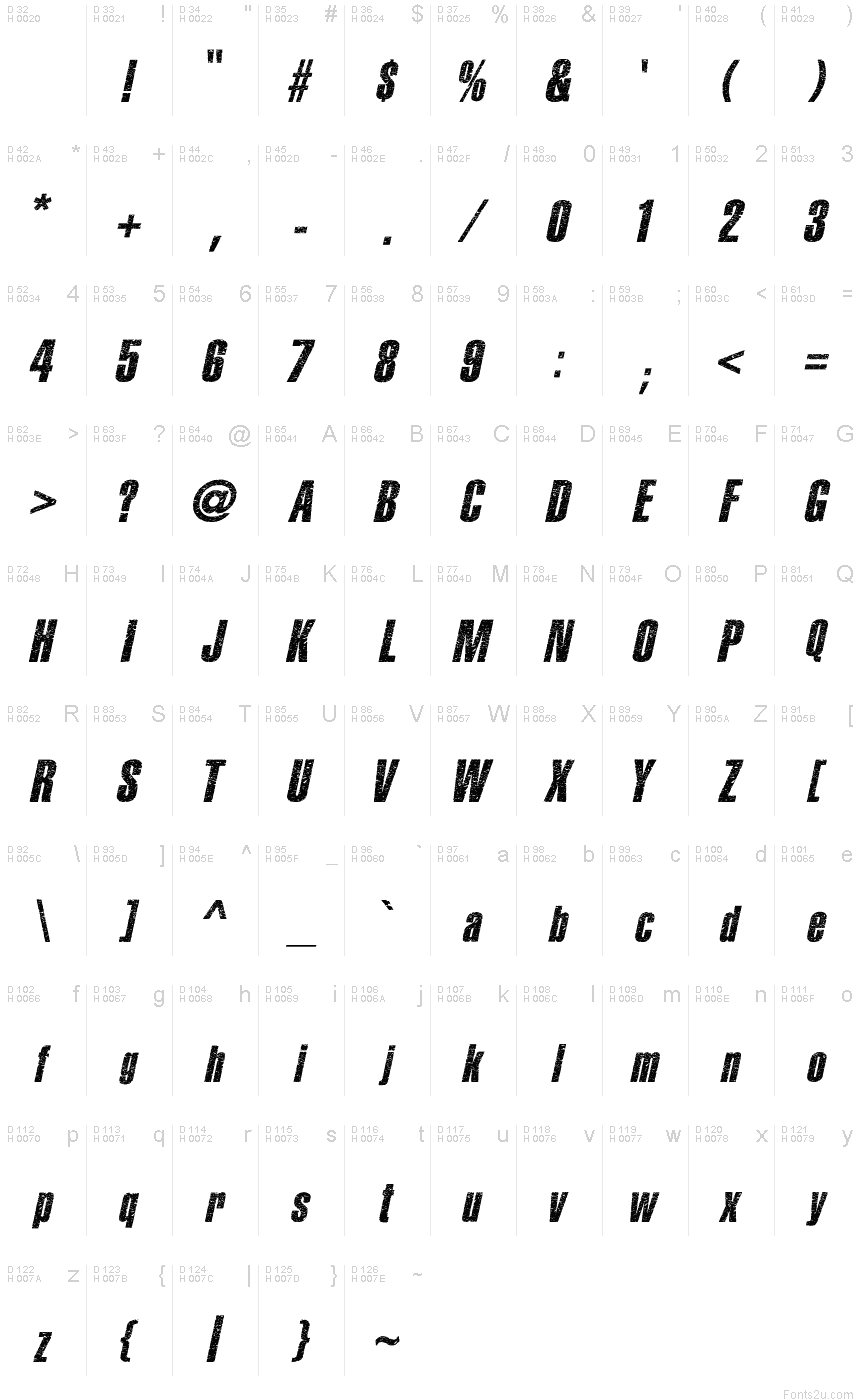
Momento Mori Oblique von John Flickinger ist eine kostenlose Display-Schrift mit einer rauen, vorwärtsdrängenden Attitüde. Die Buchstaben wirken abgenutzt und zerkratzt, als wäre die Farbe abgerieben, während die schräge Neigung und die massiven Formen für einen lautstarken und unruhigen Charakter sorgen.
Damit eignet sie sich perfekt für Horror-Plakate, Punk-Flyer, Titelkarten, Albumcover und distressed Brand-Designs, bei denen ein cleanes Finish zu zahm wirken würde. Als kostenlose Schrift für kurze Überschriften oder gestapelte Wörter bringt sie Dynamik und Zerstörung zugleich – so können schon wenige Buchstaben die Stimmung tragen.